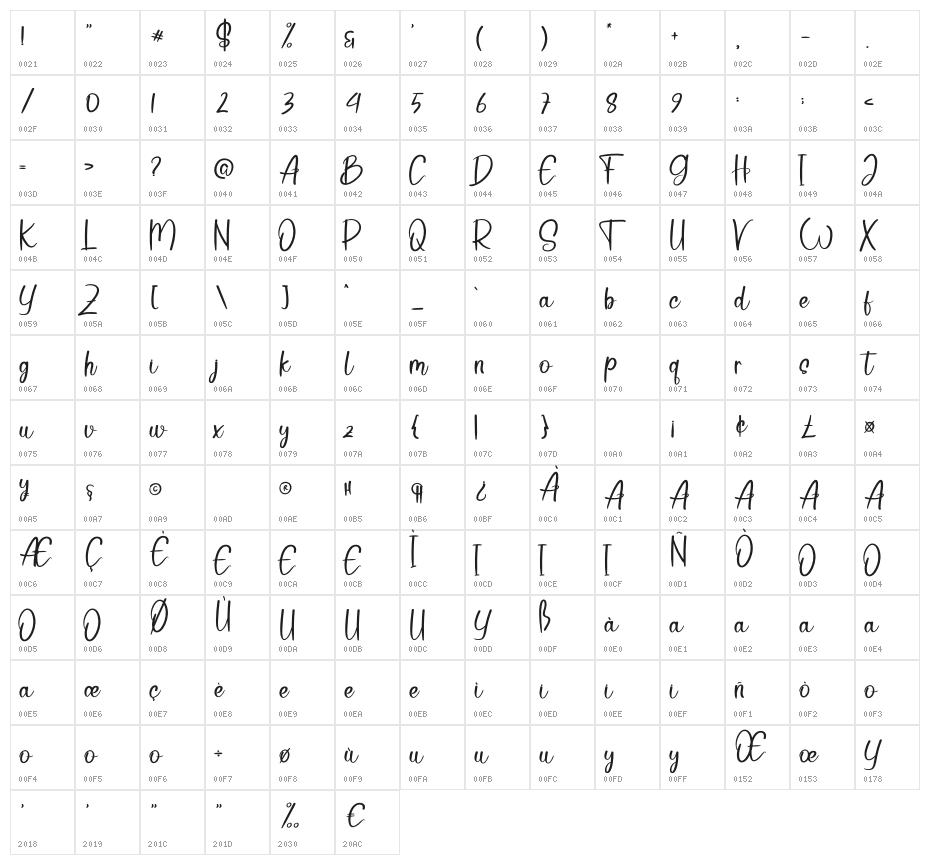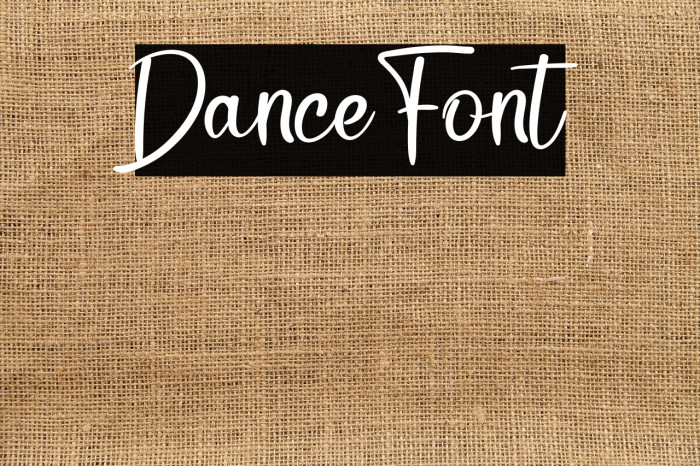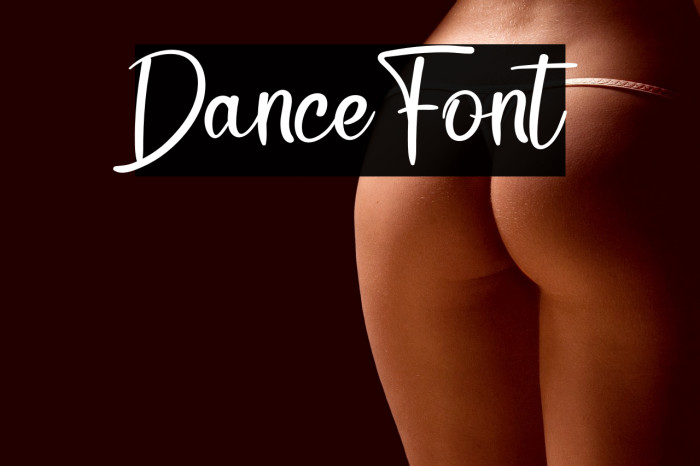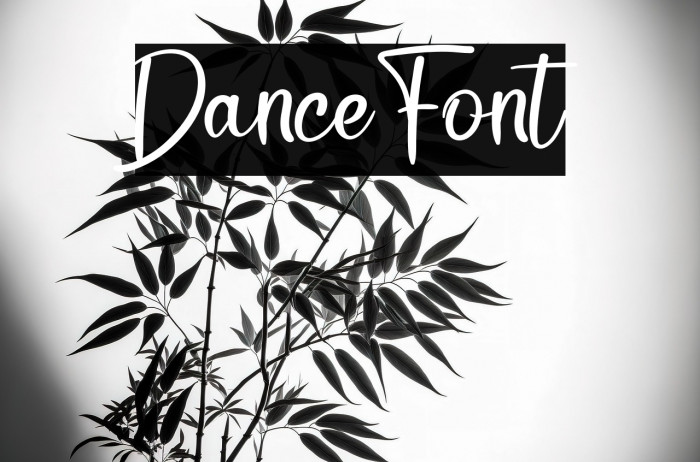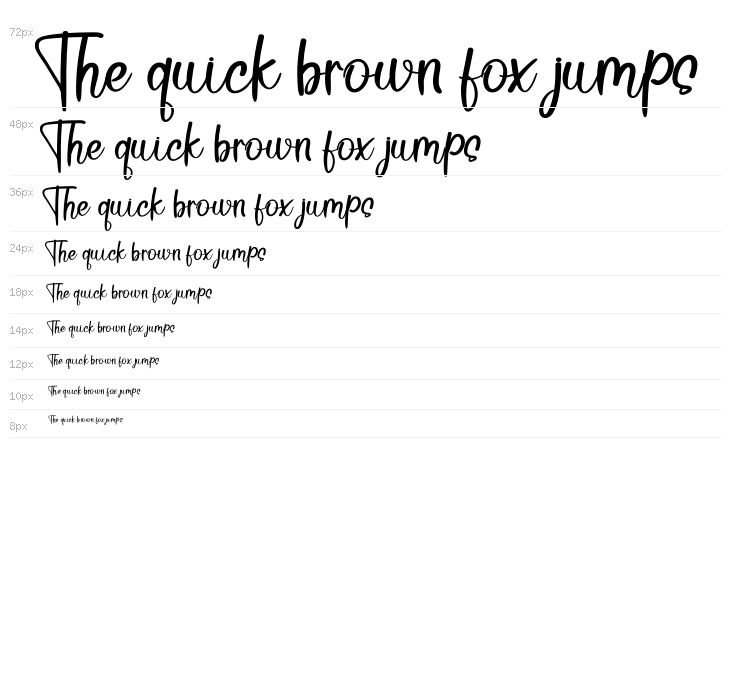
Dance Font
| Область применения | Logos, Invitations, Artistic projects |
| Рекомендуемые проекты | Ideal for wedding invitations, greeting cards, branding, and artistic projects that require a personal, elegant touch. |